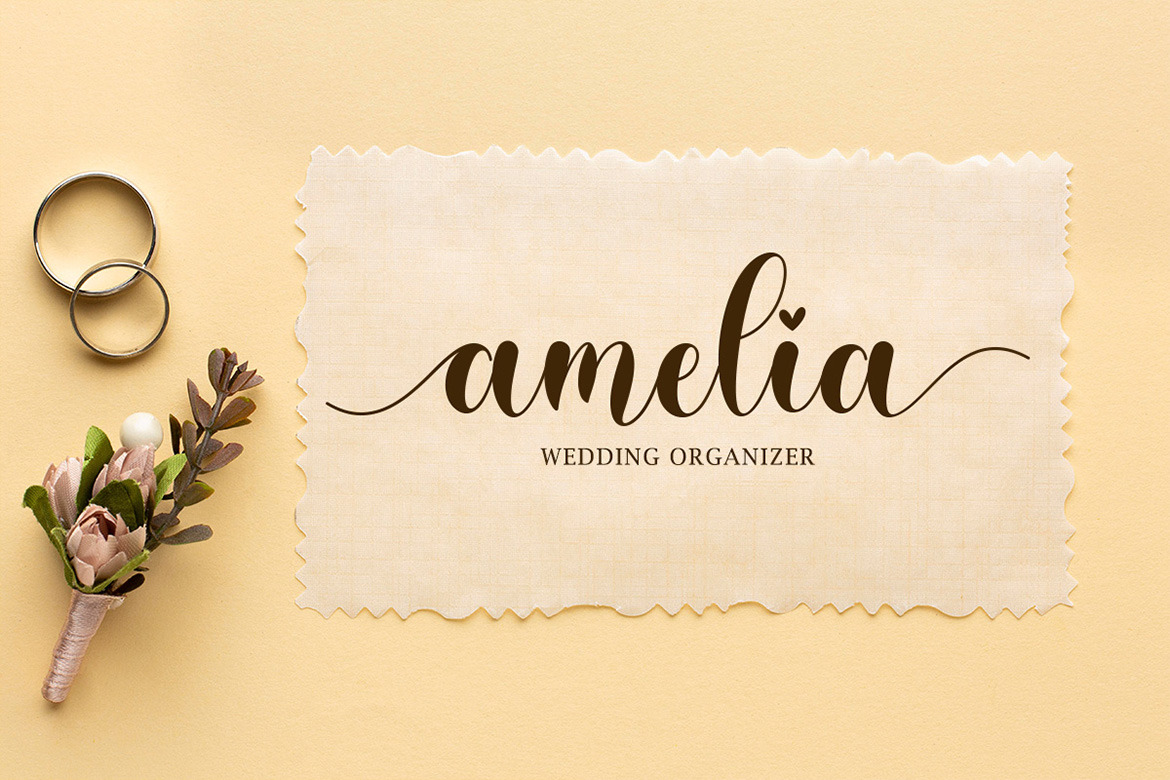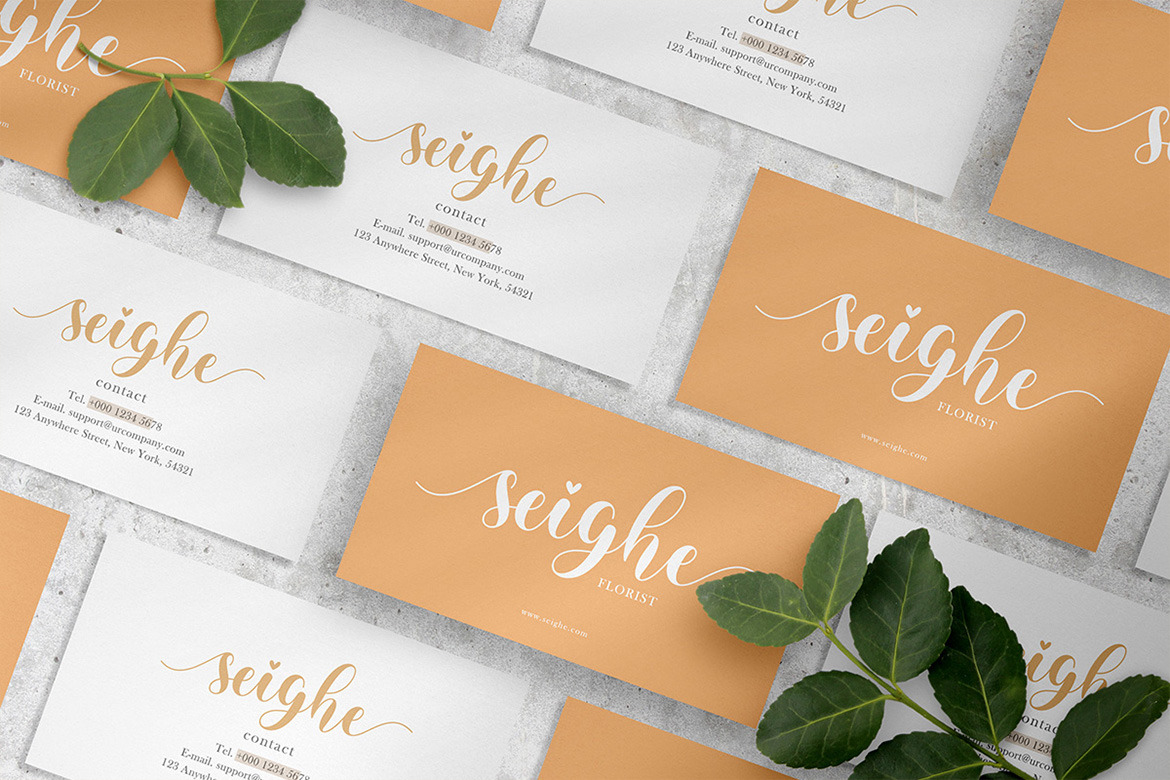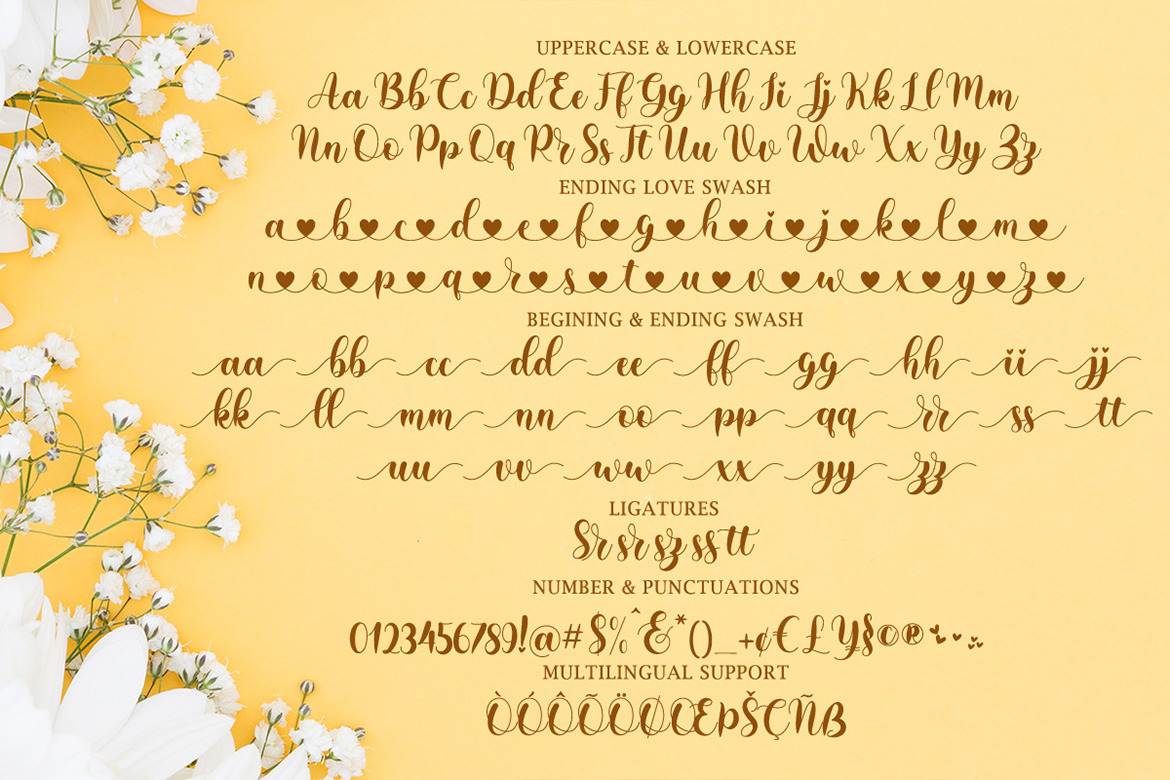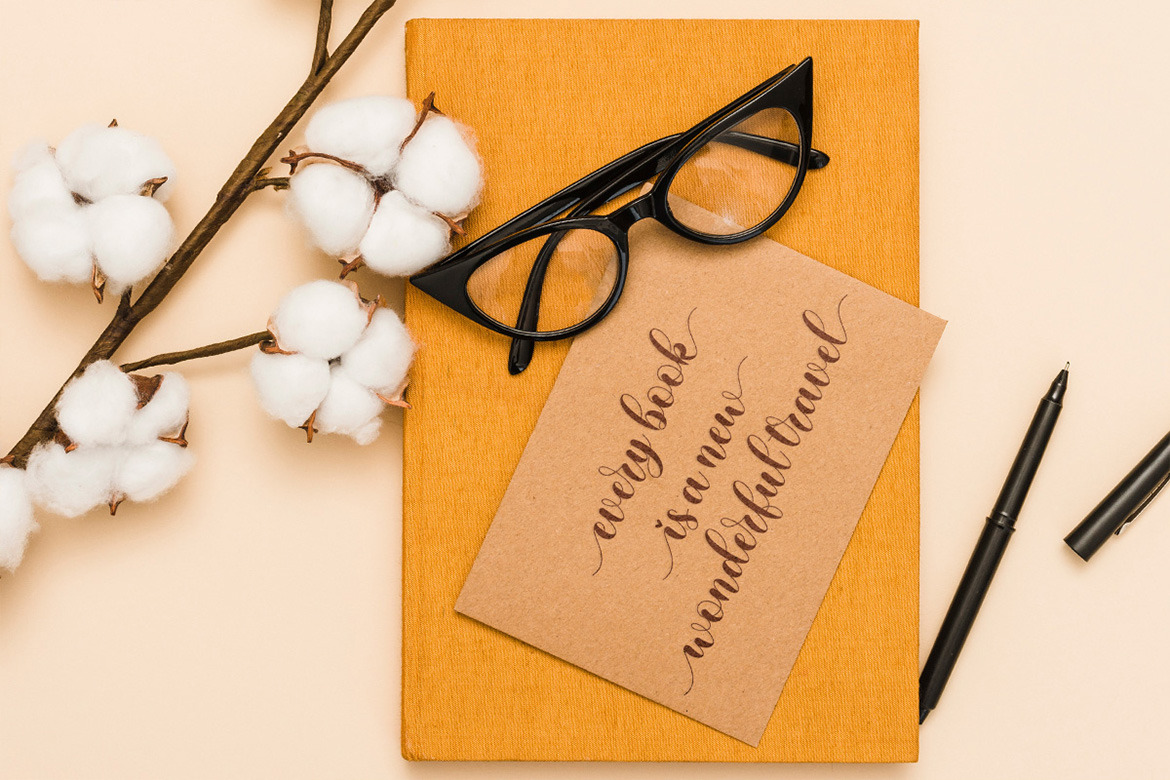
Giới thiệu về Font TF Jacky Betty Việt hóa
TF Jacky Betty Việt hóa là một font chữ viết tay (script font) nổi bật với vẻ đẹp lãng mạn, duyên dáng và đầy ngọt ngào. Font này được thiết kế với những đường nét mềm mại, bay bổng và đặc biệt là sự xuất hiện của hình trái tim ở một số ký tự (ví dụ: chữ ‘i’ hay các nét nối), tạo nên một phong cách độc đáo, đáng yêu và đầy cảm xúc.
Với sự duyên dáng và tính thẩm mỹ cao cùng những chi tiết trái tim lãng mạn, Jacky Betty là lựa chọn lý tưởng cho các thiết kế muốn truyền tải sự ngọt ngào, tình yêu và dấu ấn cá nhân:
- Thiết kế thiệp cưới: Hoàn hảo để viết tên cô dâu chú rể, lời mời, hoặc các thông tin chi tiết trên thiệp cưới. Nét chữ viết tay kết hợp với hình trái tim sẽ biến mỗi tấm thiệp thành một tác phẩm nghệ thuật, mang đậm dấu ấn cá nhân và sự lãng mạn của tình yêu.
- Thiết kế Valentine: Lý tưởng cho các tấm thiệp, poster, banner, hoặc các ấn phẩm truyền thông trong dịp Lễ Tình Nhân. Font này giúp tạo không khí ngọt ngào, lãng mạn và thể hiện tình cảm một cách dễ thương, chân thành.
- Thiết kế kỷ niệm: Phù hợp cho thiệp mời kỷ niệm ngày cưới, sinh nhật, hoặc các sự kiện cá nhân đòi hỏi sự tinh tế và cảm xúc.
- Thiết kế mạng xã hội: Tuyệt vời cho các bài đăng trên Instagram, Facebook, hoặc các story cần sự ngọt ngào và cá tính.
Với TF Jacky Betty Việt hóa, bạn có thể dễ dàng thổi hồn lãng mạn, sự tinh tế và vẻ đẹp ngọt ngào vào các thiết kế, tạo ra những sản phẩm không chỉ đẹp mắt mà còn đầy cảm xúc và sức hút đặc biệt.
Font Việt hóa TF Jacky Betty – Phong chữ tình yêu valentine